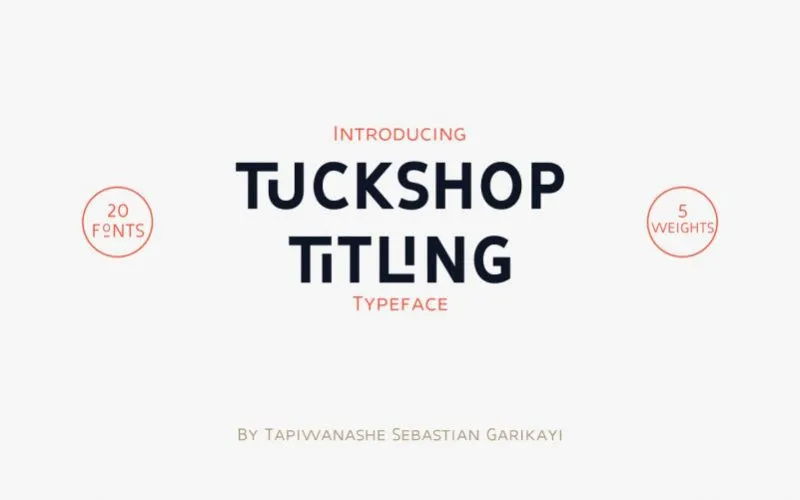
Tuckshop Titling Font Family
A Tuckshop Titling Font Family é uma família moderna e elegante de fóruns serifados que combina uma rica personalidade com uma leitura fluida. Com sete pesos e vinte fóruns, ela oferece um amplo espectro para projetos variados. Como o nome sugere, esta fonte se inspira na escrita de sinais de Tuckshop em Chinotimba, Victoria Falls, Zimbabwe. A fonte é particularmente adequada para aplicações visuais que exigem destaque, como posters, headlines e logotipos. Suas curvas suaves combinadas com linhas retas aguçadas criam um design único e memorável. Além disso, ligaturas interessantes dão a fonte uma dose divertida de personalidade que transforma qualquer projeto em algo mais cativante. Esta família é ideal para designers que procuram uma solução versátil para projetos visuais exigentes, desde criações gráficas minimalistas até elementos exuberantes e memoráveis. Tapiwanashe Garikayi, o criador desta fonte, nos oferece um produto de qualidade com uma personalidade única, perfeito para fazer qualquer projeto design surpreender. Tuckshop Titling é a escolha ideal para aqueles que buscam tanto estilo quanto legibilidade em seus projetos visuais.